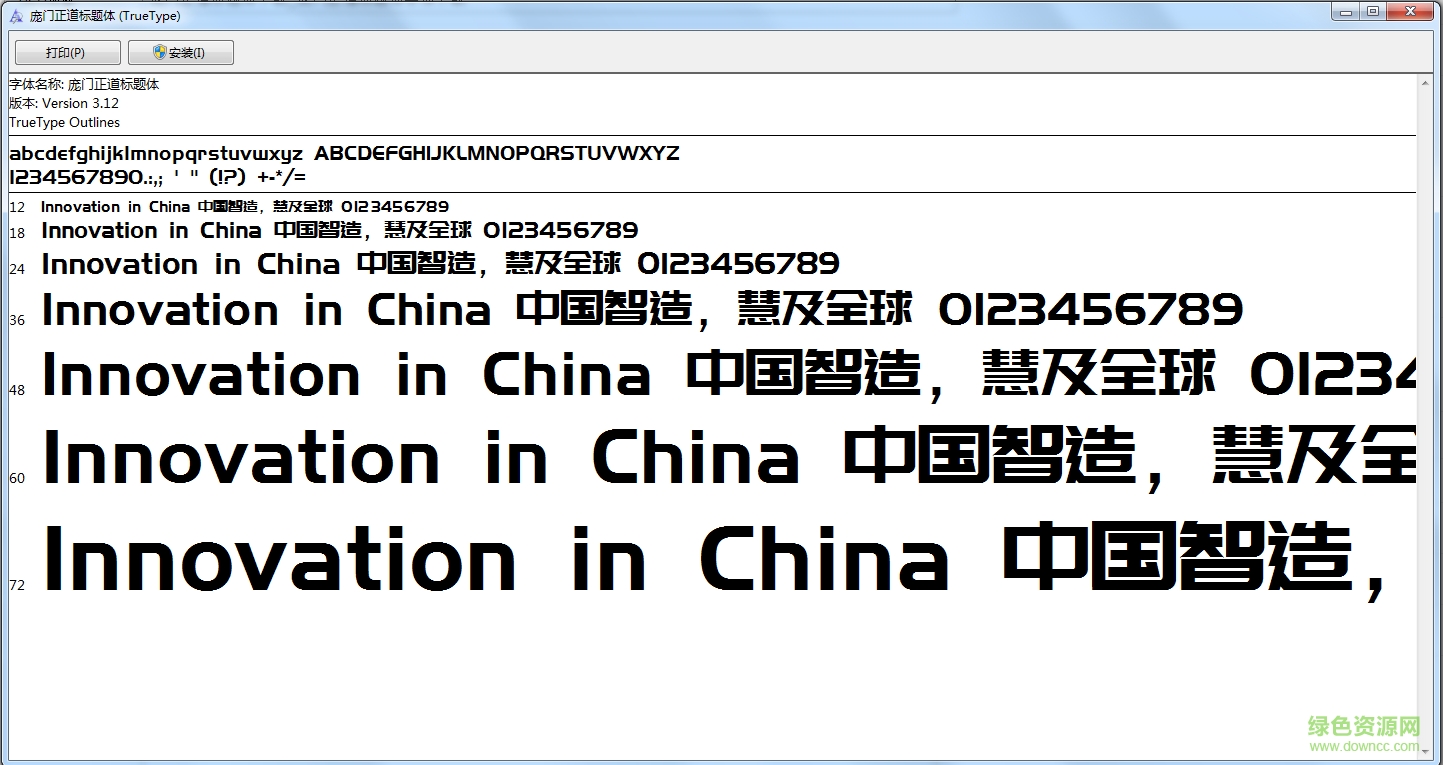
pangmenzhengdao
pangmenzhengdao字體就是龐門正道標(biāo)題體,這是一款結(jié)構(gòu)獨(dú)出心裁的字體,結(jié)構(gòu)合理,線條較粗,看起來堅(jiān)毅有大氣,可以用于動漫、科技、裝潢商品、墻報(bào)等方面,歡迎大家在綠色資源網(wǎng)下載!